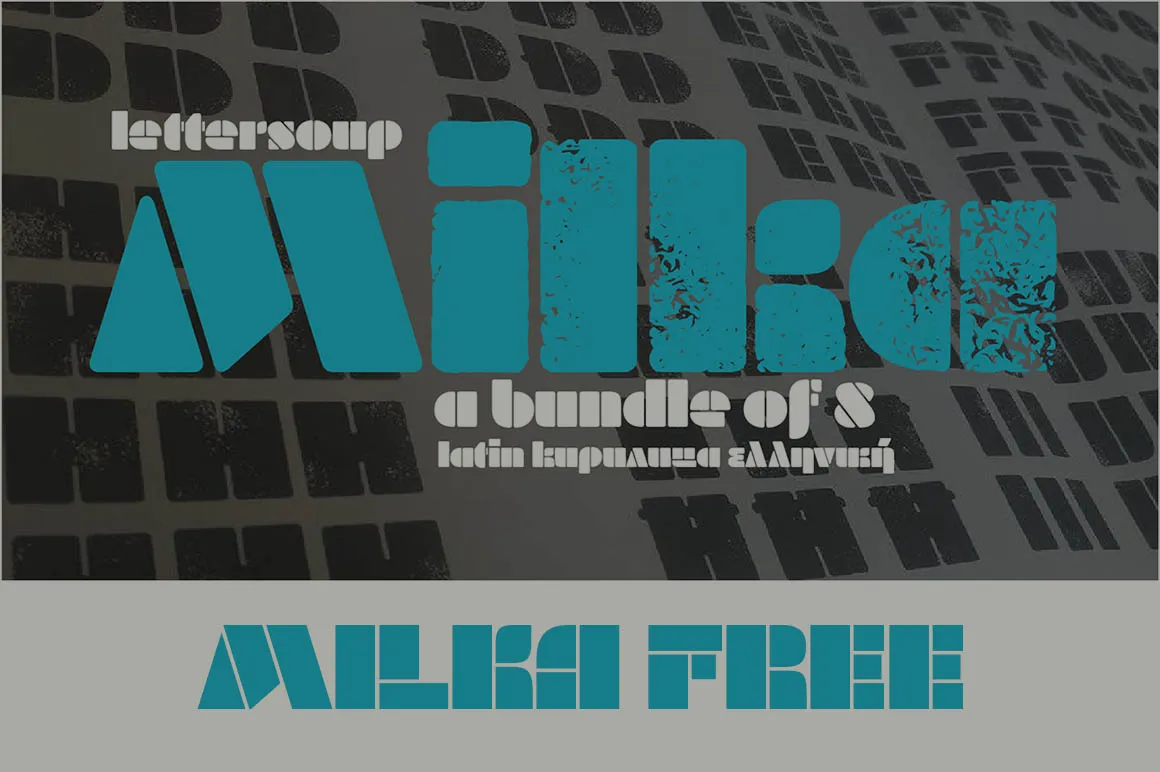
Milka Font é uma famosa família de estêncil composta por 8 estilos criada por uma equipe de designers jovens e talentosos que surgiu ao longo de mais de setenta anos, nascendo na contemporaneidade digital da arte do tipo tipográfico. Esta fonte faz parte de um vasto acervo criado como uma expansão digital sobre o famoso alfabeto desenvolvido em 1979 pela renomada artista bulgária Milka Peikova. Não há nada como a influência única e inovadora da mão de Milka, que revolucionou as ilustrações digitais e continuou a inspirar novas gerações de criadores de arte visual. Milka Font é uma experiência digital envolvente, repleta de estilo e personalidade, perfeitamente adaptada para qualquer aplicação gráfica moderna que busque criar um impacto forte e inconfundível.